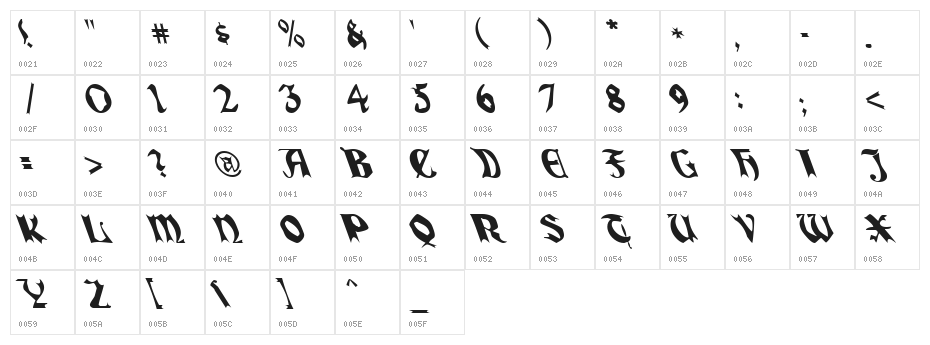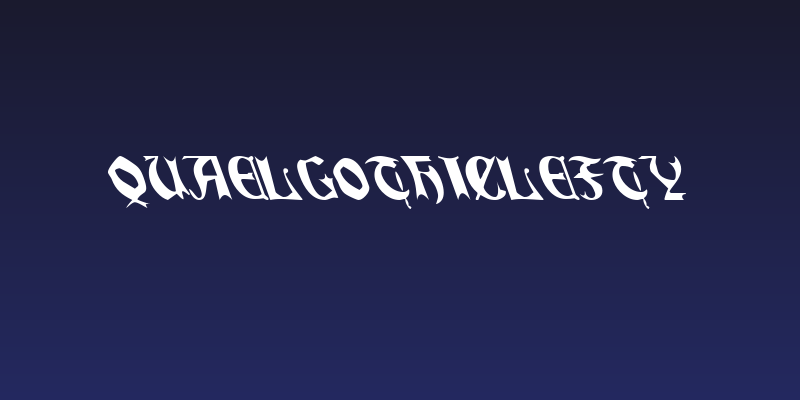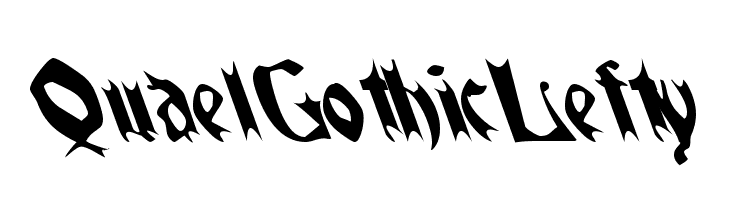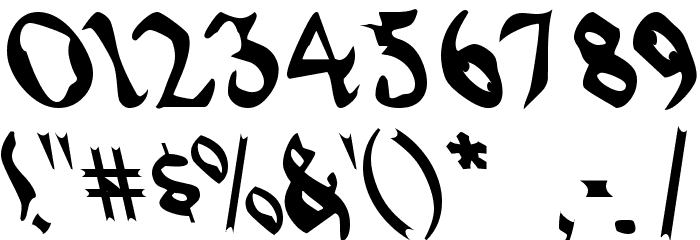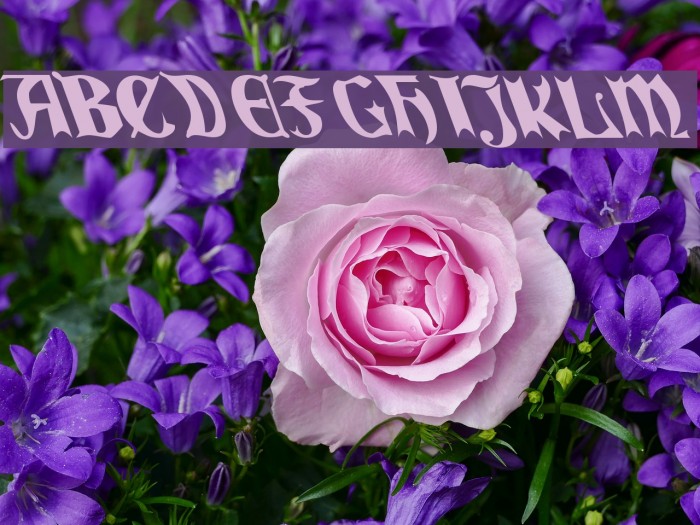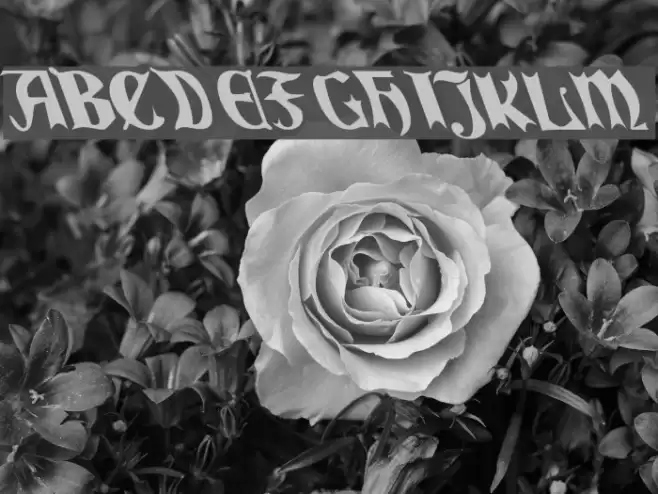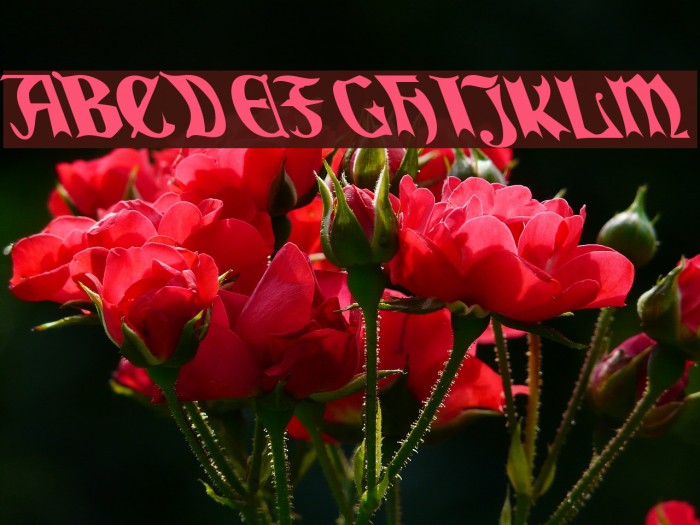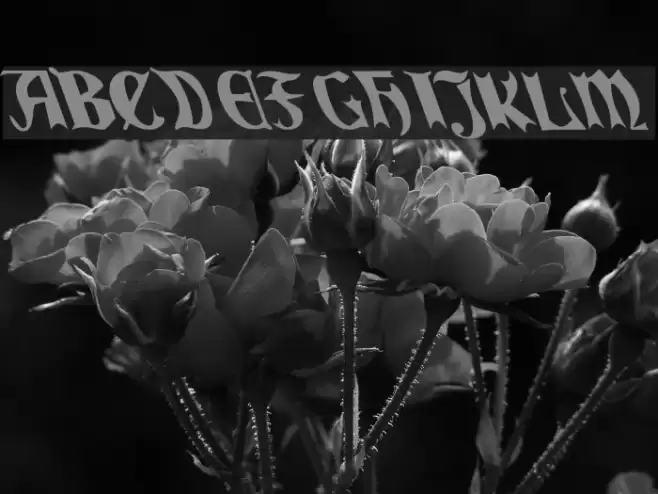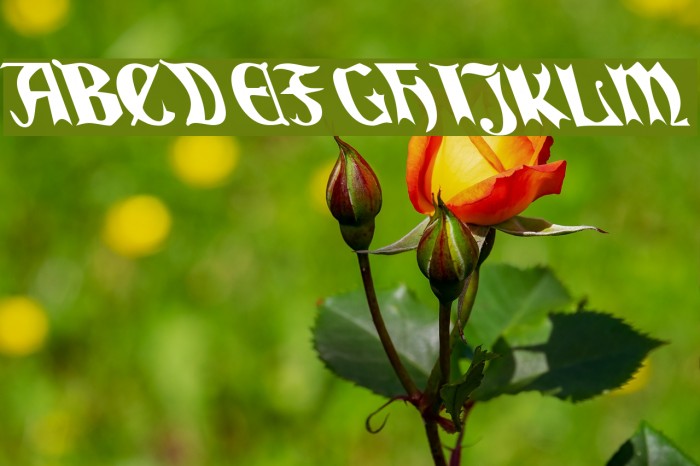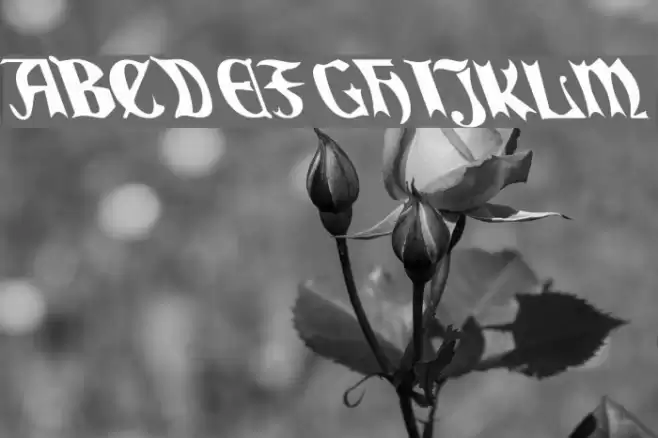
QuaelGothicLefty Font
✎ Gothic
| Style général | Gothic, Decorative |
| Projets proposés | Ideal for use in album covers, posters, branding for edgy or alternative products, and any design requiring a bold statement. |